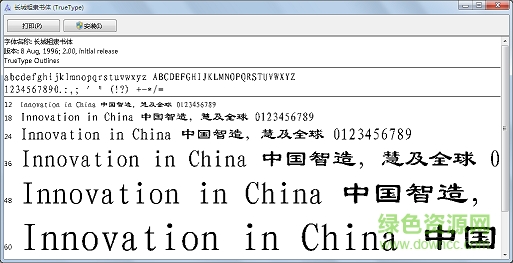
glei00b
glei00b是什么字體?glei00b(長(zhǎng)城粗隸書(shū)體)是一款極具書(shū)法藝術(shù)美的隸書(shū)字體,字形優(yōu)美,布局合理,筆畫(huà)頓挫富有變化,韻味十足 ,可以應(yīng)用于廣告設(shè)計(jì)、期刊雜志、ppt等領(lǐng)域!
隸書(shū)字體介紹
隸書(shū),有秦隸、漢隸等,一般認(rèn)為由篆書(shū)發(fā)展而來(lái),字形多呈寬扁,橫畫(huà)長(zhǎng)而豎畫(huà)短,講究“蠶頭雁尾”、“一波三折”。根據(jù)出土簡(jiǎn)牘,隸書(shū)起源于戰(zhàn)國(guó)。傳說(shuō)程邈作隸,漢隸在東漢時(shí)期達(dá)到頂峰,對(duì)后世書(shū)法有不可小覷的影響,書(shū)法界有“漢隸唐楷”之稱(chēng)。